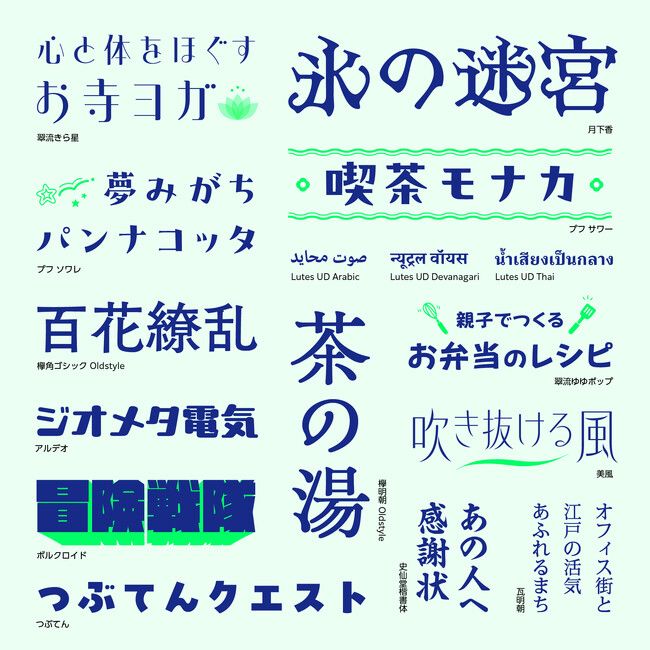
モリサワ 2023年度新書体として「欅明朝 Oldstyle」や「ボルクロイド」「プフ サワー」など個性派が揃う16点を新規にリリース
株式会社モリサワは2023年秋にリリースする新書体の一部を発表した。リリース予定の新書体は、広告や動画テロップなど、印象的な見出しに映えるデザイン書体を多く取り揃えた、個性豊かな16ファミリー。
パワフルでエッジの効いた作風の「ボルクロイド」、ミステリアスな意匠の「月下香(げっかこう)」、幾何学的な骨格に丸みのあるエレメントを組み合わせた「アルデオ」、そして可愛らしい太ゴシック風デザイン書体「つぶてん」、オールドスタイルの書体である「欅(けやき)明朝 Oldstyle」、「欅角ゴシック Oldstyle」、統一しすぎない自由な字形と小さめの字面が昨年好評だった「プフ」シリーズから、新たに「プフ サワー」、「プフ ソワレ」。
台湾の玉川設計所が手掛ける繁体字フォントをベースに制作され、涼やかで洗練された雰囲気をまとう「美風(みかぜ)」や台湾の子会社であるArphic Typesの書体の漢字を組み合わせた「翠流(すいりゅう)きら星」と「翠流ゆゆポップ」、毎日新聞社が開発した「瓦明朝」や品位や信頼感がある太楷書体として「史仙堂(しせんどう)楷書体」が加わる。
和文書体以外にも、欧文フォント「Lutes UD PE」の多言語展開としてThai / Arabic / Devanagari(デーヴァナーガリー)が新たに加わる。「Lutes UD」シリーズは、デジタルデバイス上での視認性に配慮し、ローコントラストかつクリアですっきりとした印象のセリフ体。各言語の文字の特色を活かしながら本シリーズで多言語を展開することにより、デザインの一貫性を持たせることができる。これらを合わせた16点が追加になる。